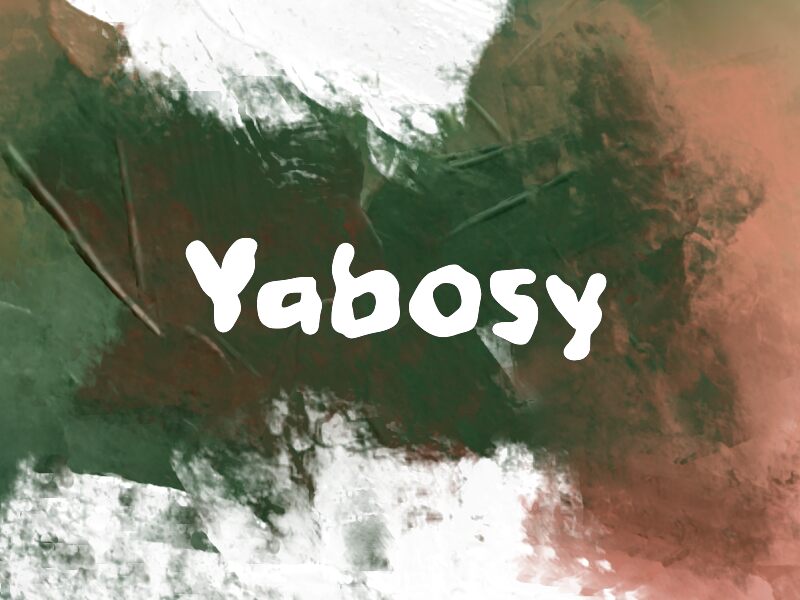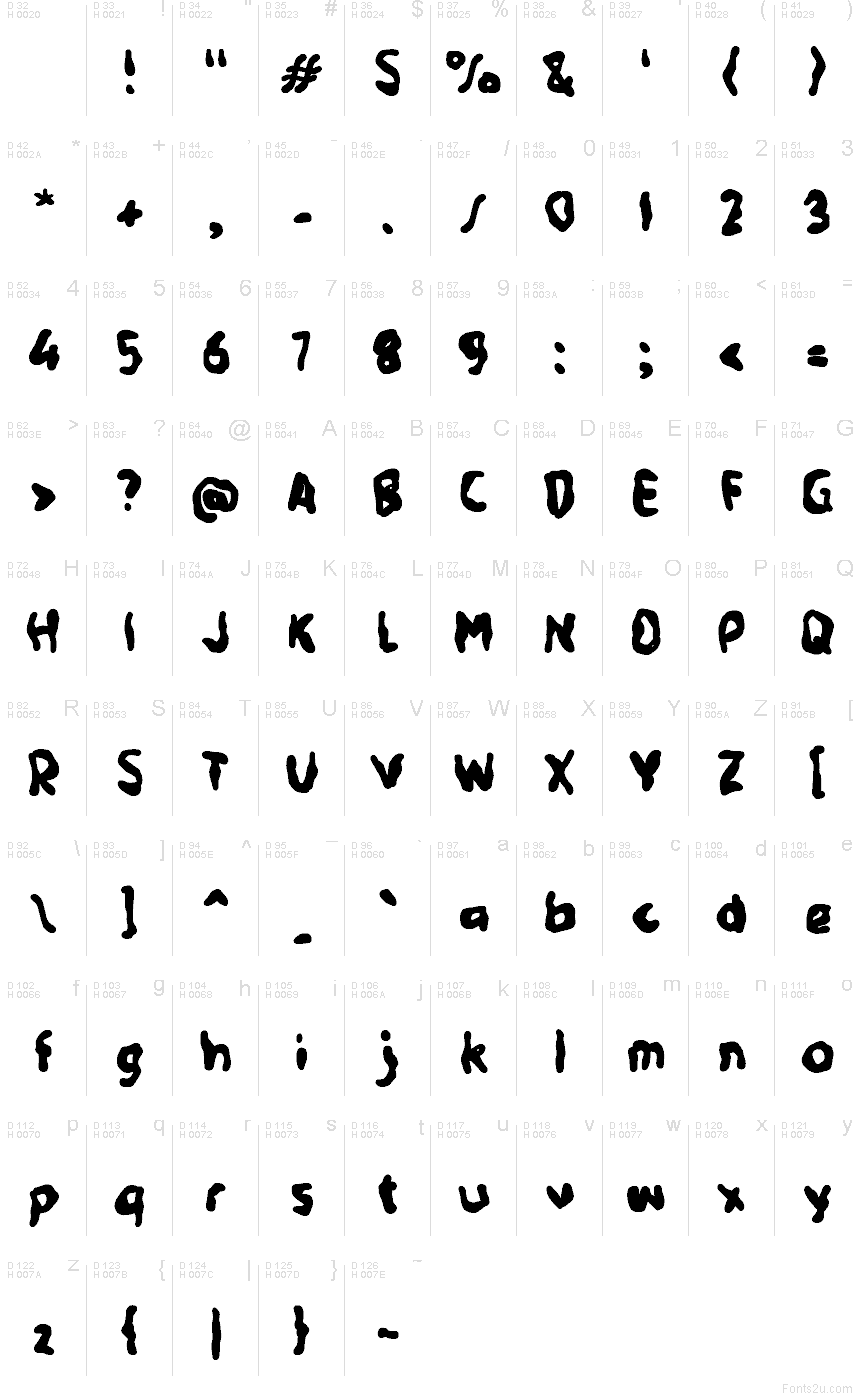
Yabosy
Yabosy, da Wep, é uma fonte brush gratuita moldada por letras arredondadas e volumosas que parecem ter sido pintadas com batidinhas, em vez de desenhadas com precisão. A silhueta macia e irregular dá ao design uma textura de tinta gomosa, com bordas imperfeitas e espaços internos desiguais que mantêm o estilo despojado e artesanal.
Esse ritmo amplo e orgânico torna a Yabosy uma escolha natural para títulos de cartazes, embalagens de snacks, flyers de eventos infantis, design de adesivos e gráficos lúdicos para redes sociais. Palavras curtas ficam especialmente convincentes quando você busca uma presença marcante e pintada que pareça casual e tátil, em vez de algo liso ou geométrico.